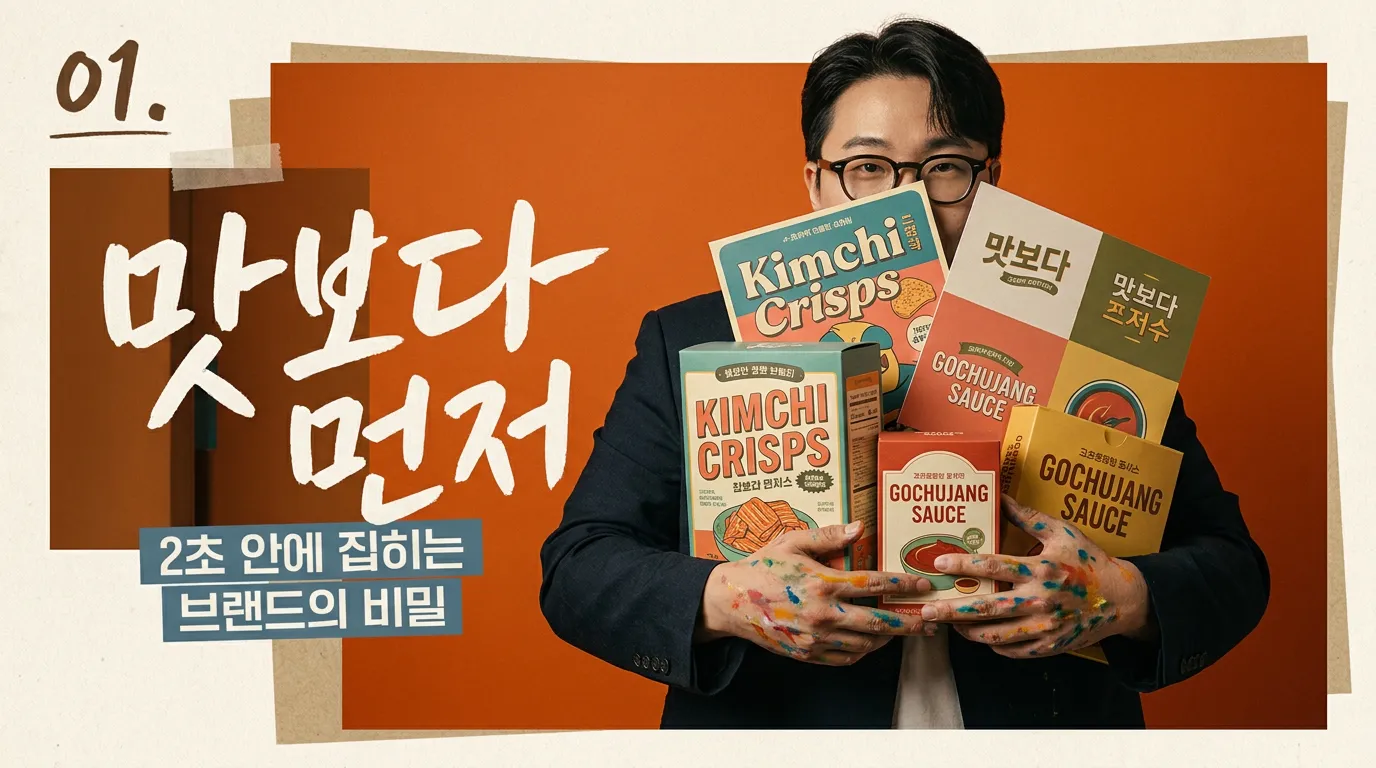
식품 브랜드 로고 디자인, 색·폰트 조합 7개만 바꿔도 ‘맛’이 먼저 보입니다
식품 브랜드 로고 디자인에서 구매욕구를 만드는 색상·서체 조합 7가지. 제품군별로 바로 적용할 실무 기준을 정리했습니다.
마트 진열대에서 2초 안에 집히는 제품은, 맛 설명보다 색과 글자가 먼저 일합니다.
빨강은 무조건 맛있어 보일까요?
빨강은 식품 브랜드 로고에서 가장 많이 떠올리는 색입니다. 매운맛, 육즙, 즉각적인 반응을 만들기 쉽죠. 그런데 전부 빨강으로 밀면 싸 보이거나 자극만 남습니다.
저라면 빨강을 메인으로 쓰더라도 폰트는 굵은 고딕 하나로 정리합니다. 떡볶이, 소스, 육가공처럼 ‘한 입의 힘’이 필요한 제품에 맞습니다. 대신 자간을 너무 좁히지 마세요. 숨 막히는 로고가 됩니다.
최근 한식 소스 패키지 색채 연구에서도 원재료와 음식이 연상되는 색이 패키지에 많이 쓰였고, 식품 색상이 구매 의욕과 마케팅에 영향을 줄 수 있다고 봤습니다. 결국 빨강 자체보다 ‘무슨 맛의 빨강인가’가 먼저입니다. (kci.go.kr)
건강식품은 왜 초록만 쓰면 심심해질까요?
초록은 채소, 자연, 저당, 비건, 클린라벨과 잘 맞습니다. 문제는 초록에 얇은 산세리프를 붙이면 병원 보조제처럼 보일 때가 많다는 겁니다.
추천 조합은 세이지 그린 + 둥근 산세리프입니다. 단백질바, 그래놀라, 비건 간식, 이유식에 좋습니다. 여기에 크림색을 넓게 깔면 ‘건강하지만 맛없는’ 인상을 줄일 수 있습니다.
비건식품 패키지 연구에서도 색채와 라벨이 소비자 태도와 구매의도에 연결된다는 점을 다뤘습니다. 건강식품 로고는 착해 보이는 데서 끝나면 안 됩니다. 먹고 싶어 보여야 팔립니다. (dbpia.co.kr)
달콤한 제품은 어떤 글자가 더 먹히나요?
초콜릿, 쿠키, 디저트는 갈색만으로 부족합니다. 갈색은 맛을 설명하지만, 구매 버튼을 누르게 하는 건 질감입니다.
다크 브라운 + 부드러운 세리프를 써보세요. 프리미엄 초콜릿, 베이커리, 수제 잼에 잘 맞습니다. 반대로 캐주얼한 젤리나 아이스크림은 파스텔 핑크 + 둥근 볼드체가 낫습니다.
초콜릿 패키지 연구에서는 형태, 색채, 문구 같은 디자인 요소와 구매의도의 관계를 살폈습니다. 저는 여기서 하나를 더 봅니다. 달콤한 식품은 로고 획 끝이 너무 날카로우면 맛보다 가격표가 먼저 보입니다. (kci.go.kr)
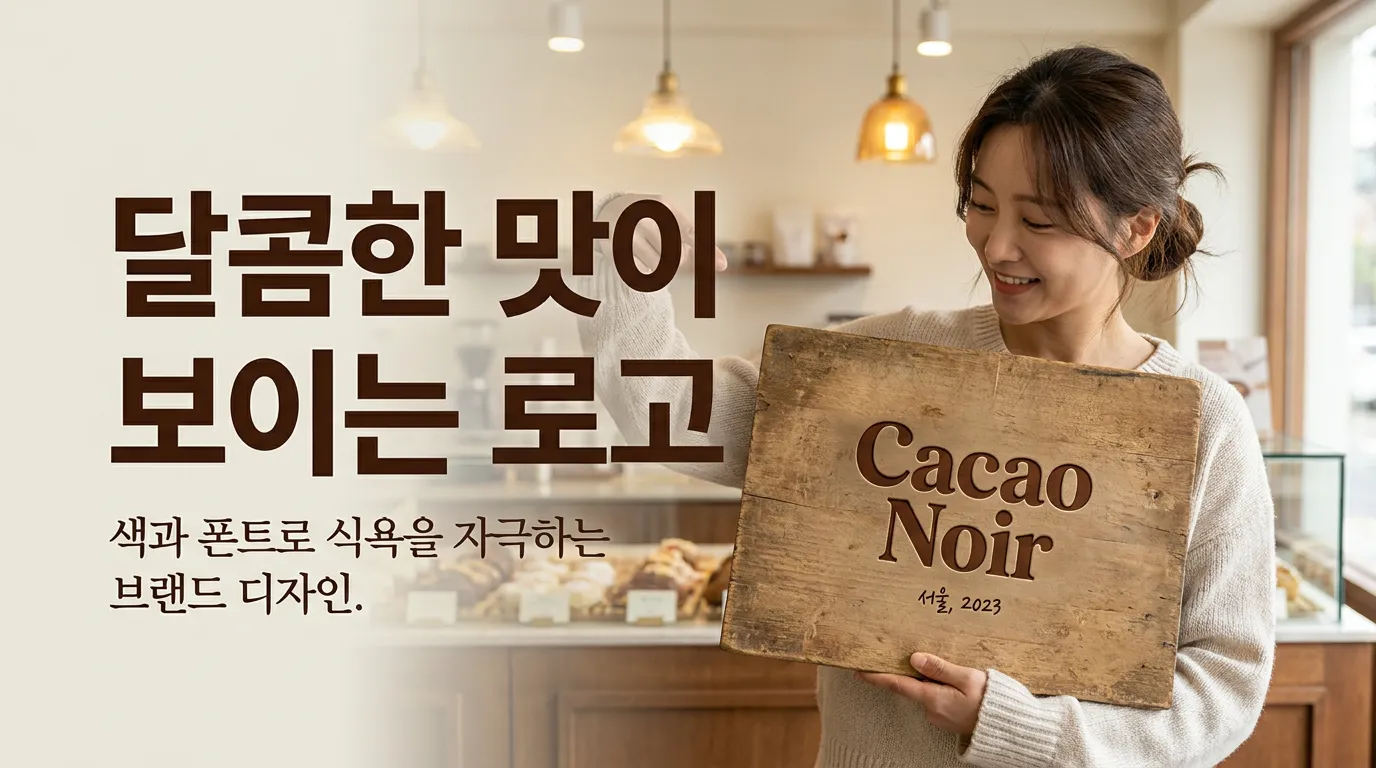
시원한 음료는 파랑만 쓰면 될까요?
음료, 생수, 이온음료는 파랑·하늘색 계열이 강합니다. 하지만 식품 전체로 보면 파랑은 식욕을 낮춰 보일 위험도 있습니다. 그래서 ‘차갑다’와 ‘맛있다’를 같이 설계해야 합니다.
아이스 블루 + 기울어진 고딕은 스포츠음료, 탄산수, 기능성 음료에 맞습니다. 여기에 라임색 포인트를 넣으면 청량감이 살아납니다. 커피 RTD라면 갈색 + 흰색 + 단단한 산세리프가 더 안전합니다.
스포츠 이온음료 연구에서는 구매 행동에서 브랜드 이미지 영향이 컸고, 색채 선호가 난색·한색으로 뚜렷하게 나뉜다고 분석했습니다. 색은 맛뿐 아니라 ‘마시는 상황’을 정합니다. (kci.go.kr)
7가지 조합, 어디에 바로 쓰면 될까요?
정리하면 이렇게 잡으면 됩니다. 매운 소스는 레드 + 굵은 고딕. 건강 간식은 세이지 그린 + 둥근 산세리프. 프리미엄 디저트는 다크 브라운 + 세리프. 어린이 간식은 옐로 + 통통한 라운드체. 냉장 음료는 아이스 블루 + 기울어진 고딕. 전통식품은 먹색 + 절제된 명조. 가정간편식은 오렌지 + 읽기 쉬운 고딕.
마크에서 식품 브랜드 로고를 잡을 때도 색을 예쁘게 고르는 순서로 가지 않습니다. 먼저 ‘어떤 진열대에서 누구 손에 집힐지’를 정하고, 그다음 색과 폰트를 좁힙니다.
식품 브랜드 로고 디자인은 맛의 번역입니다. 제품 사진 없이도 바삭한지, 신선한지, 진한지, 가벼운지 보여야 합니다.